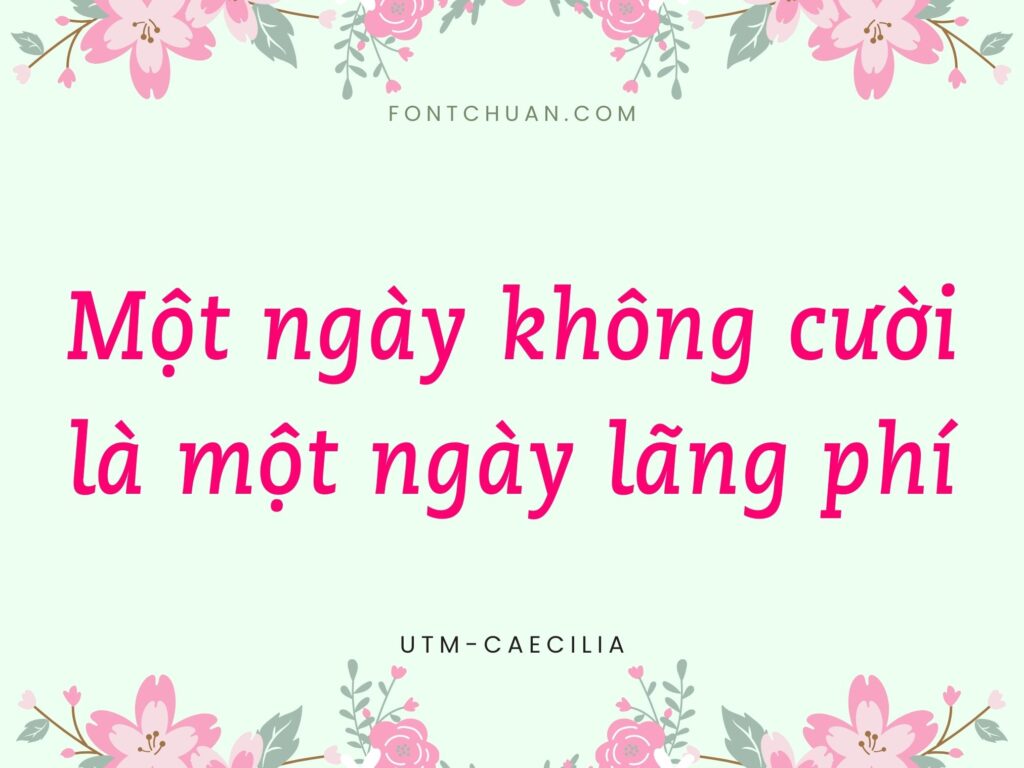
Font UTM Caecilia Kt Việt Hóa
Việt hóa bởi: Đinh Kiên
UTM Caecilia là phiên bản Việt hóa của font chữ PMN Caecilia, một Font Slab-Serif được thiết kế bởi Peter Matthias Noordzij và phát hành bởi Linotype vào năm 1990. Font này nổi bật với các ký tự có độ dày đồng đều, các nét chữ rõ ràng và dễ đọc, tạo cảm giác hiện đại và chuyên nghiệp. Phiên bản Việt hóa đã được thực hiện bởi Đinh Kiên, hỗ trợ đầy đủ tiếng Việt cùng hơn 100 ngôn ngữ khác. Đây là một trong những font được cộng đồng thiết kế sưu tầm và chọn lọc nhằm đáp ứng nhu cầu đa dạng trong thiết kế. Bên cạnh đó, UTM Caecilia cũng có thể kết hợp linh hoạt với Font Monospace trong các dự án kỹ thuật số, giúp tăng tính rõ ràng và chuyên nghiệp khi trình bày văn bản hoặc tài liệu kỹ thuật.
UTM Caecilia có cấu trúc chữ với các nét thẳng và độ dày đồng nhất, tạo nên sự hài hòa và dễ đọc. Font này phù hợp cho các ứng dụng như thiết kế tiêu đề, văn bản dài, tài liệu in ấn và các ấn phẩm yêu cầu sự rõ ràng và chuyên nghiệp. Các ngành nghề như quảng cáo, giáo dục, công nghệ và bất động sản có thể tận dụng UTM Caecilia để tạo điểm nhấn độc đáo trong thiết kế.